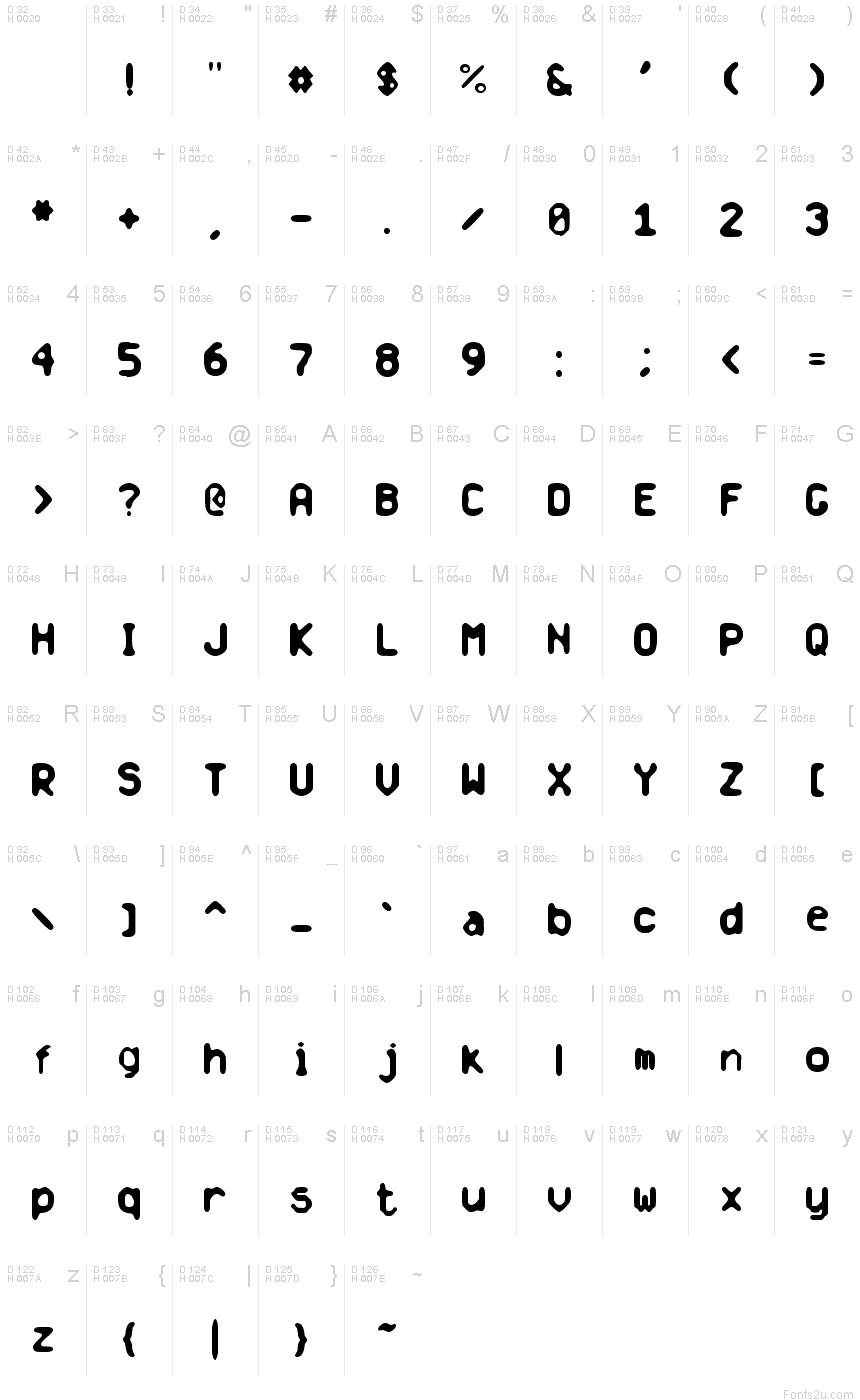
Banausia 字体
Banausia
Andrew Hungerford
由 Zogoz Design 的 Andrew Hungerford 设计的 Banausia 是一款免费的展示型字体,具有奇妙的粘稠手绘墨迹感和独特的侵蚀效果。每个字母看起来都像是用粗湿记号笔书写后又经过磨损,为文字增添了一种既友好又略带不羁的个性。其圆润厚实的字形保证了良好的可读性,而不规则的轮廓则恰到好处地增添了粗犷感,使其既不会显得过于甜腻,也不流于俗套。
使用 Banausia,您可以创作出醒目且充满活力的标题,非常适合用于音乐会海报、独立杂志、儿童活动传单、独立游戏菜单、街头潮流图形以及趣味包装设计。这款免费字体在大字号下表现尤为出色,能充分展现其墨迹斑点和凹凸质感。建议将 Banausia 与简洁的几何无衬线字体搭配用于正文,强烈的对比能让这份随性魅力恰如其分地发挥作用:在标题中。